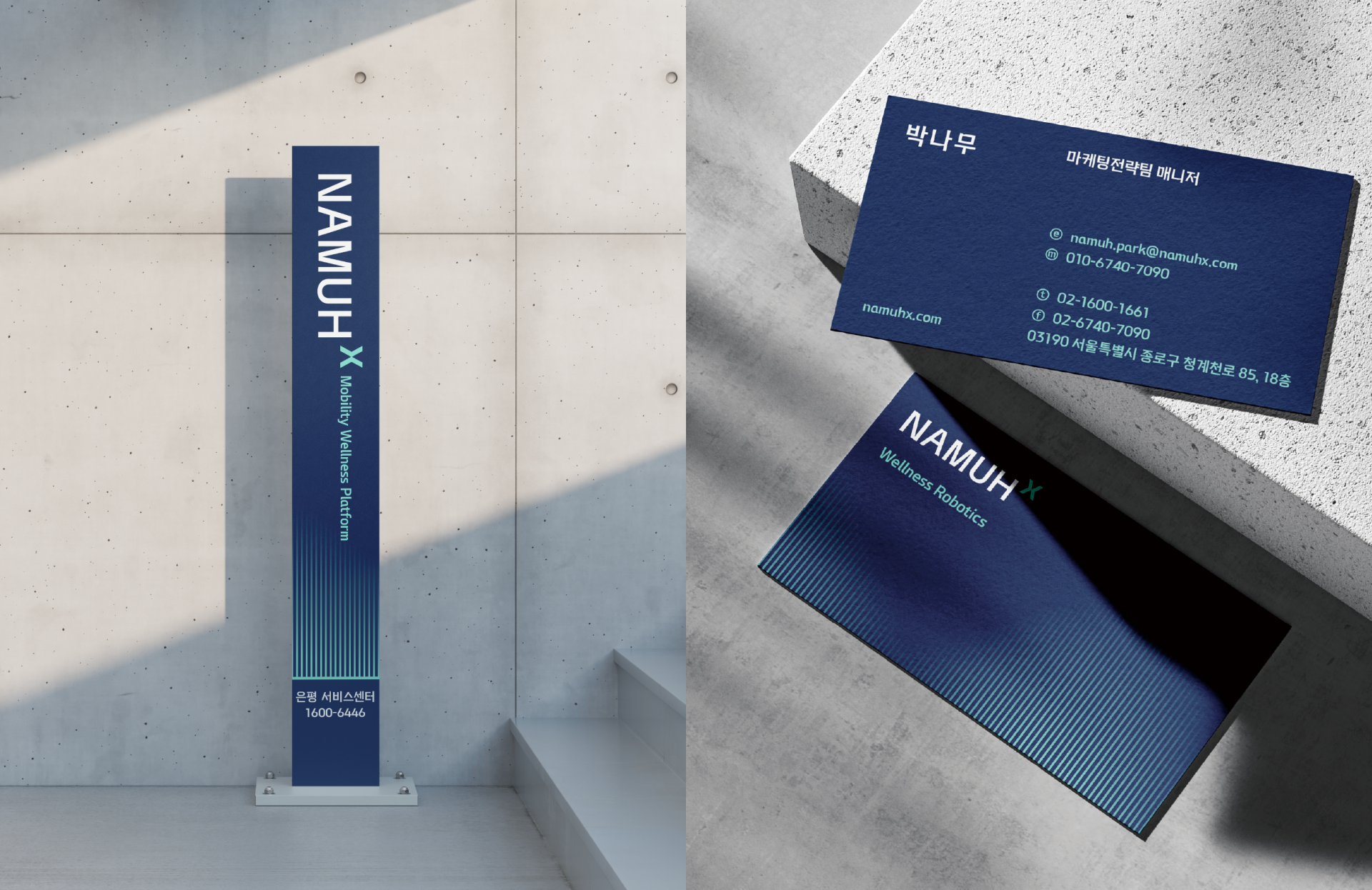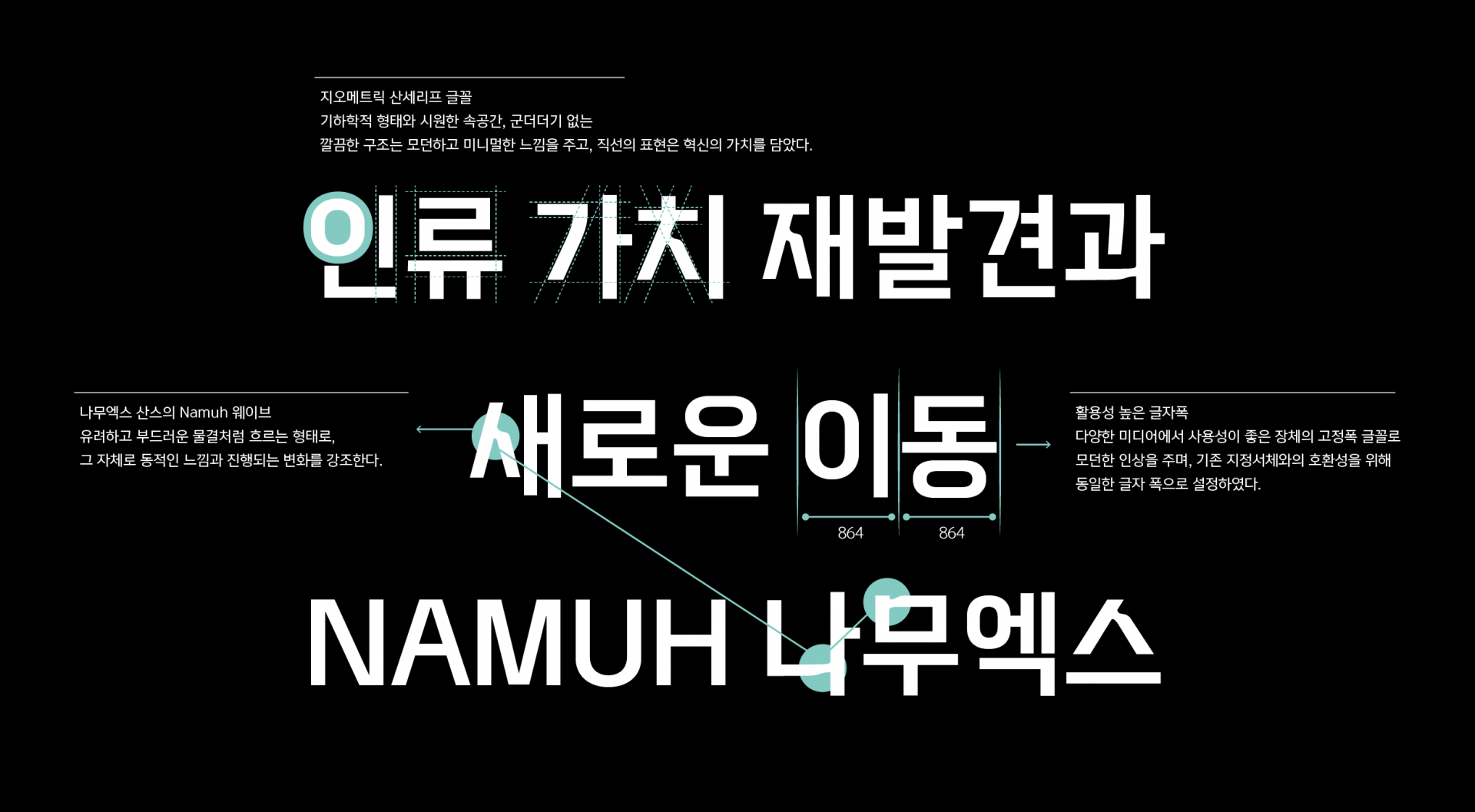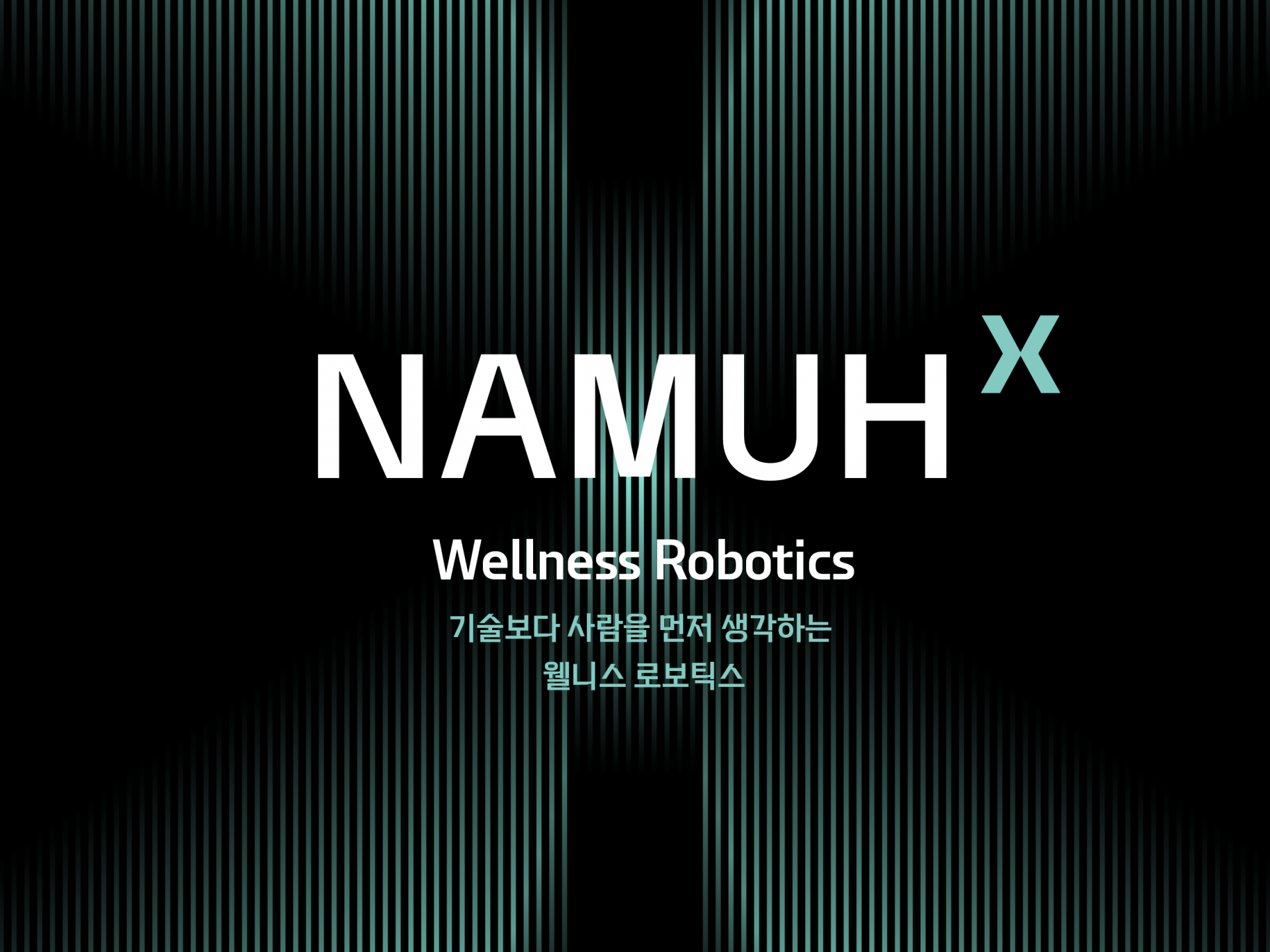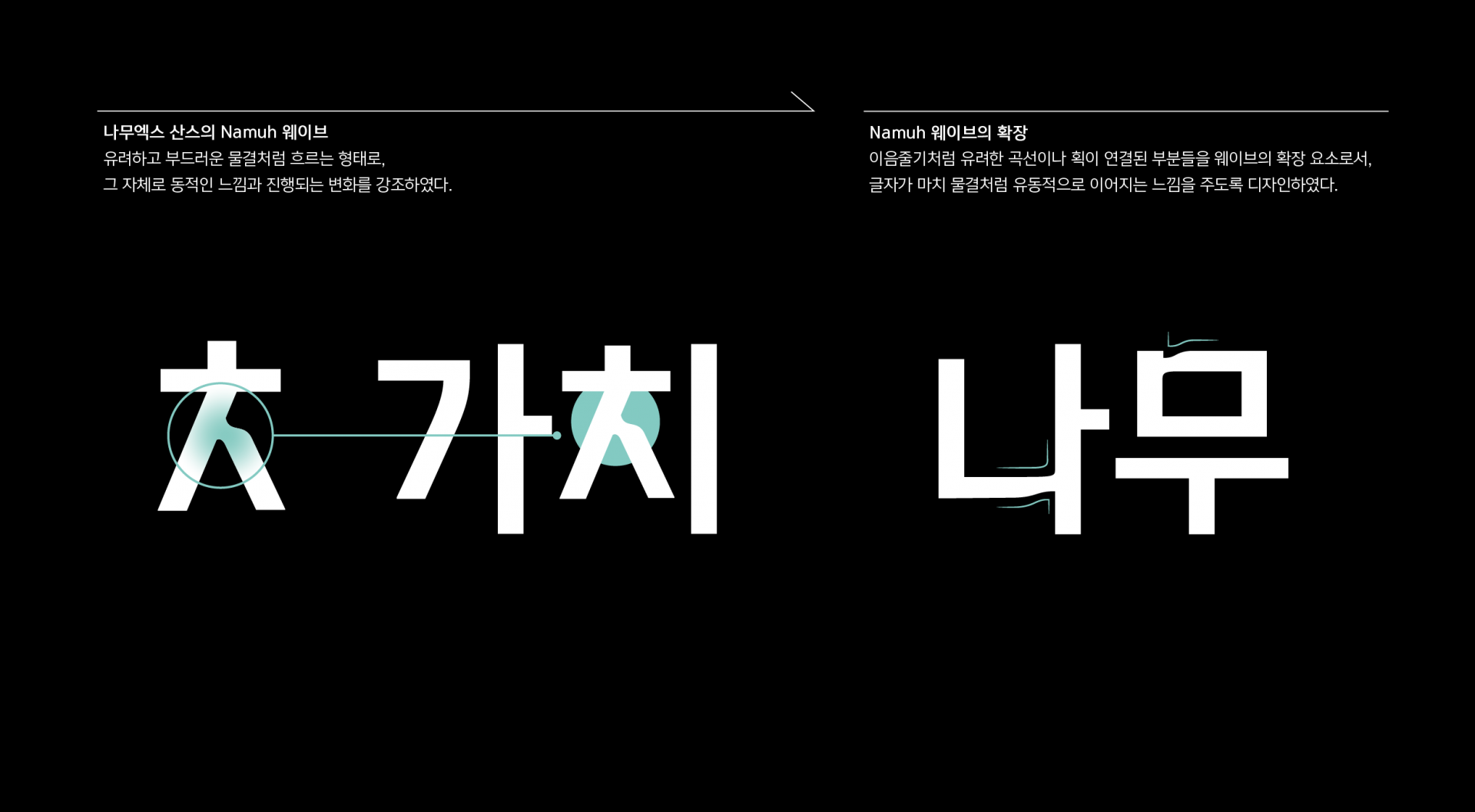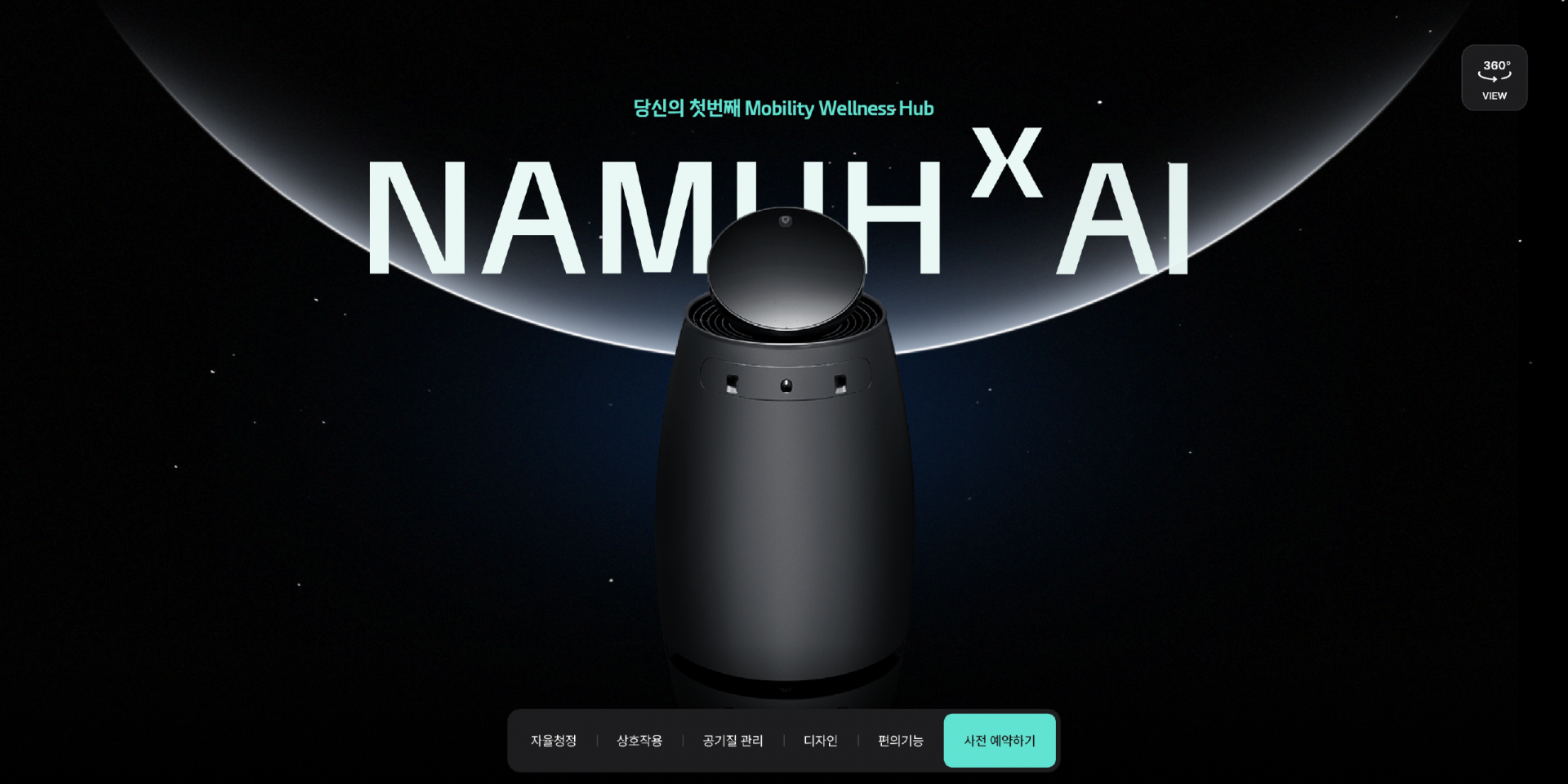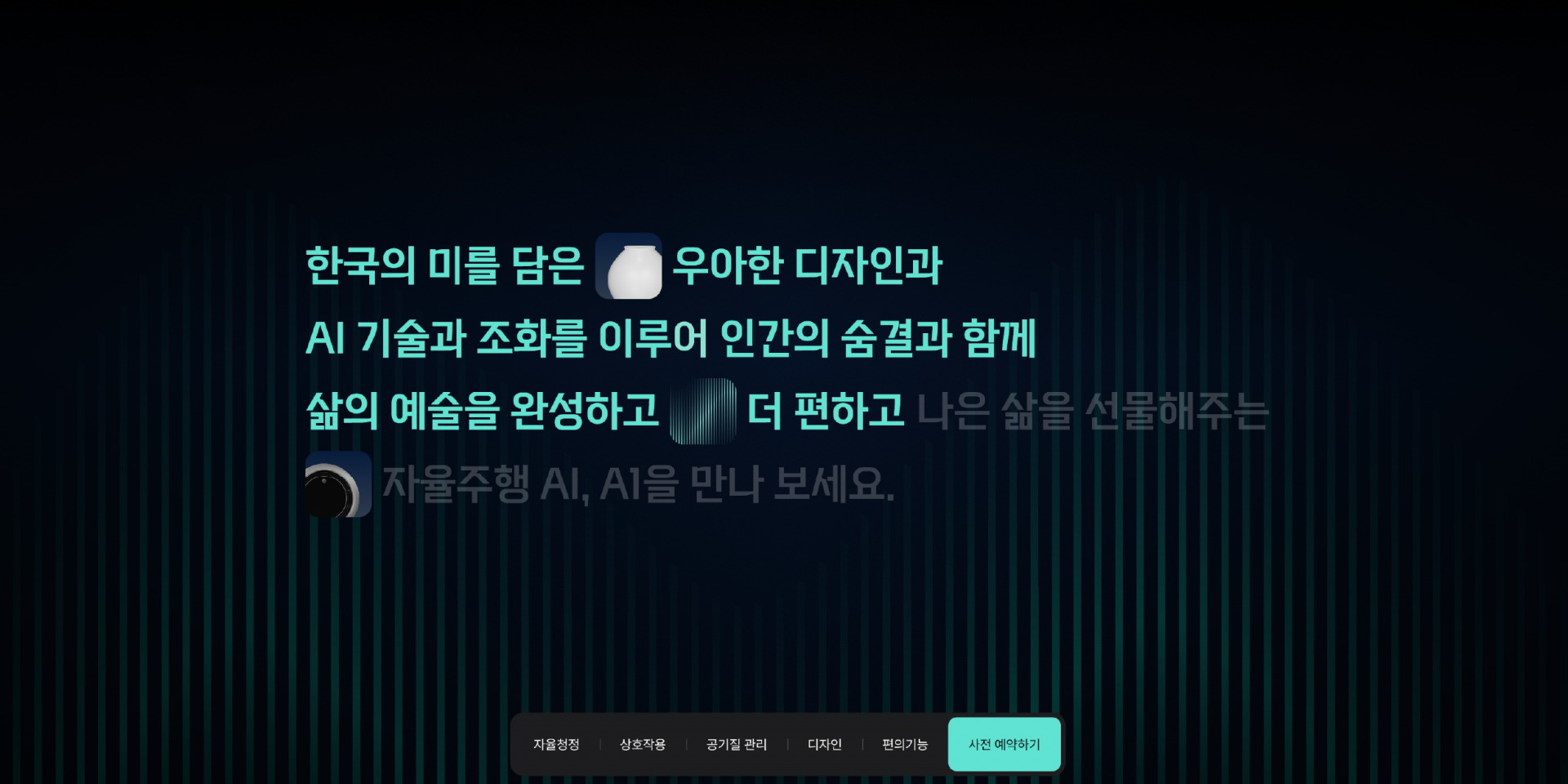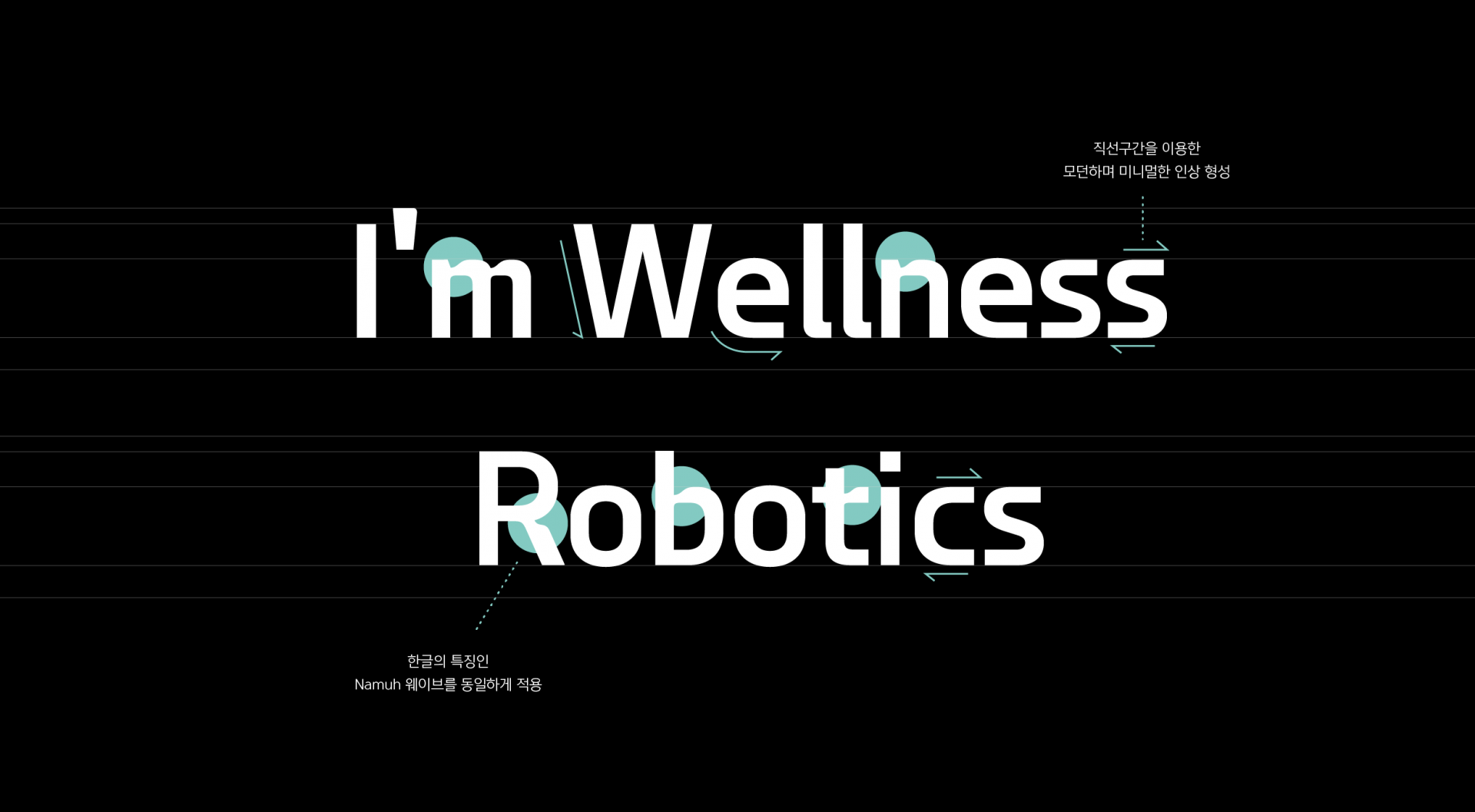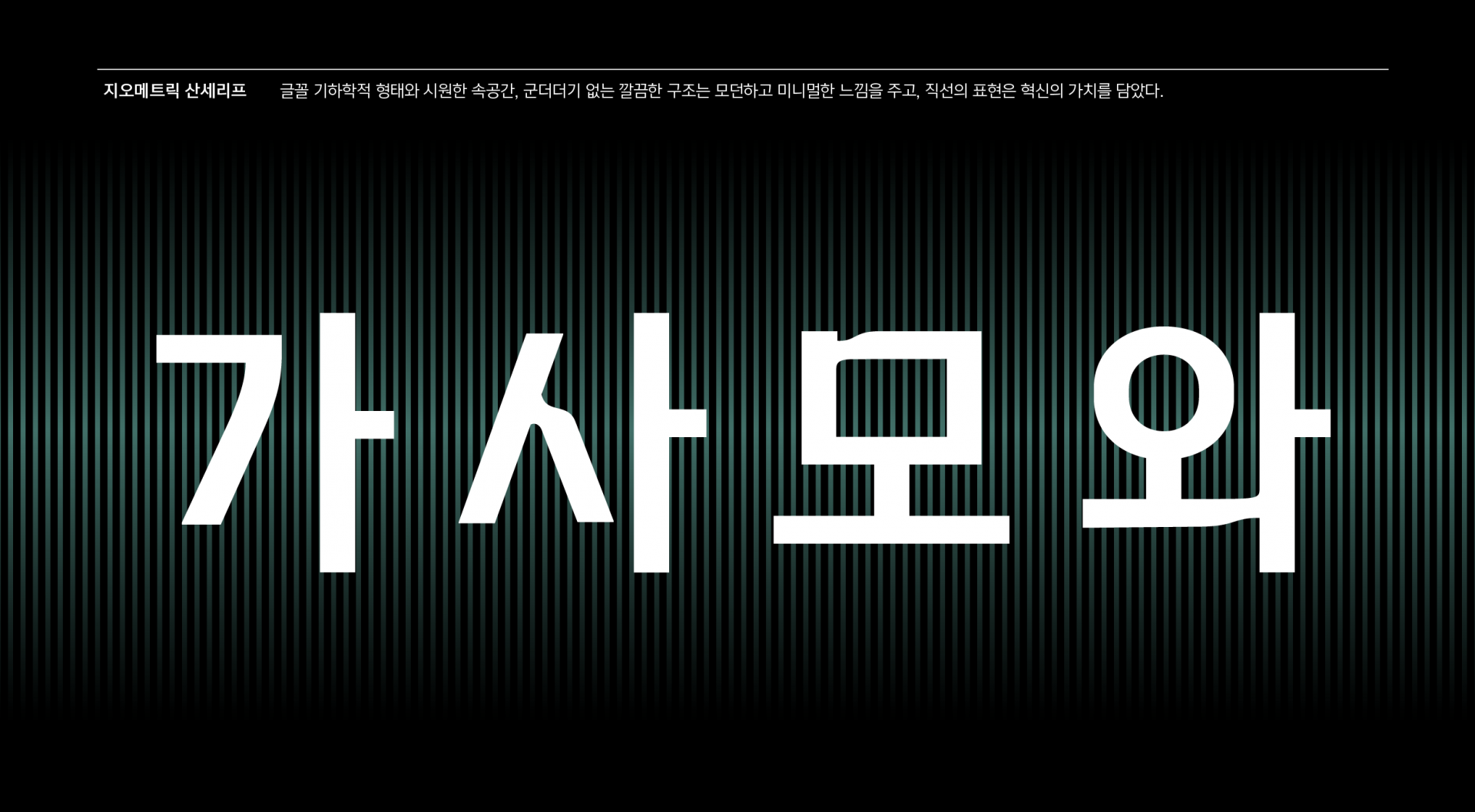
SK인텔릭스 [나무엑스]
어떤 환경에서도 이질감 없이 맞춤형 서비스를 전달하는 나무엑스의 기술력에 초점을 맞춰 단단한 뼈대와 시원한 속공간을 토대로 한 군더더기 없는 고딕체를 설계했다. 특히 '과'같은 형태에서 필획의 느낌을 최소화해 중성적 이미지를 연출했다. 낱자와 낱자를 연결, 연속성을 보여주는 이음줄기는 인간과 기술을 연결하여 웰니스라는 삶의 이정표를 제시하는 나무엑스의 철학에 기반한다.